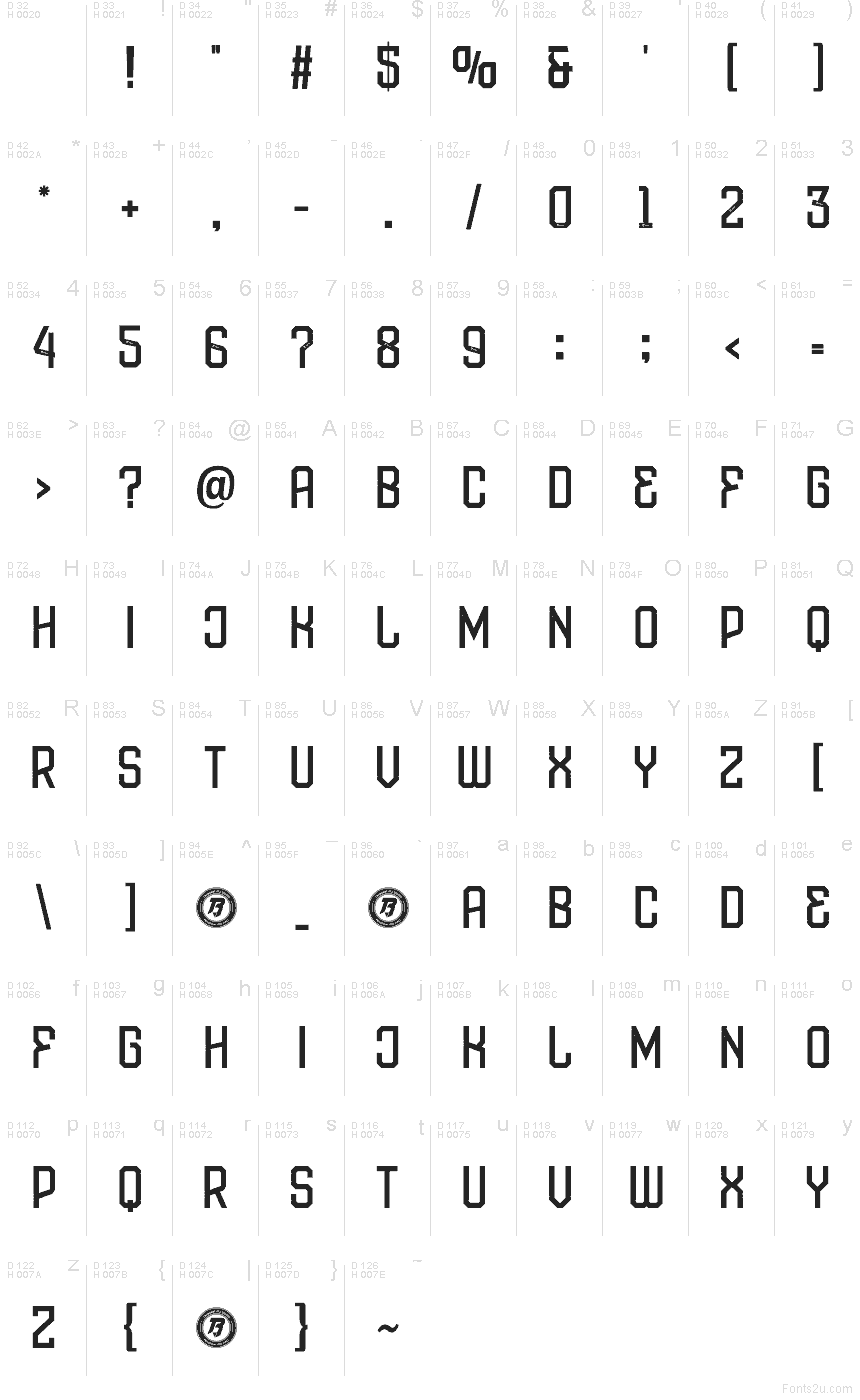
Eindhoven XII, creata da Muhammad Afif Ersya di Trequartista Studio, è un font techno gratuito che trasforma la geometria pulita in pura attitudine. Le sue forme modulari e slanciate evocano la segnaletica tagliata al laser: angoli stretti, curve nette e spaziatura ritmica che risultano nitide anche quando le lettere si incastrano. Il risultato è futuristico ma non caotico, con un tocco tecnico ed elegante in ogni linea.
Con Eindhoven XII otterrai risultati d'impatto per loghi esport, poster sci-fi, flyer per eventi tech, schermate di app, packaging di prodotti, miniature YouTube e grafiche per il gaming. Questo font gratuito brilla nei grandi formati, dove i dettagli angolari possono respirare; abbinalo a un sans serif neutro per il testo principale per mantenere il layout incisivo e leggibile.